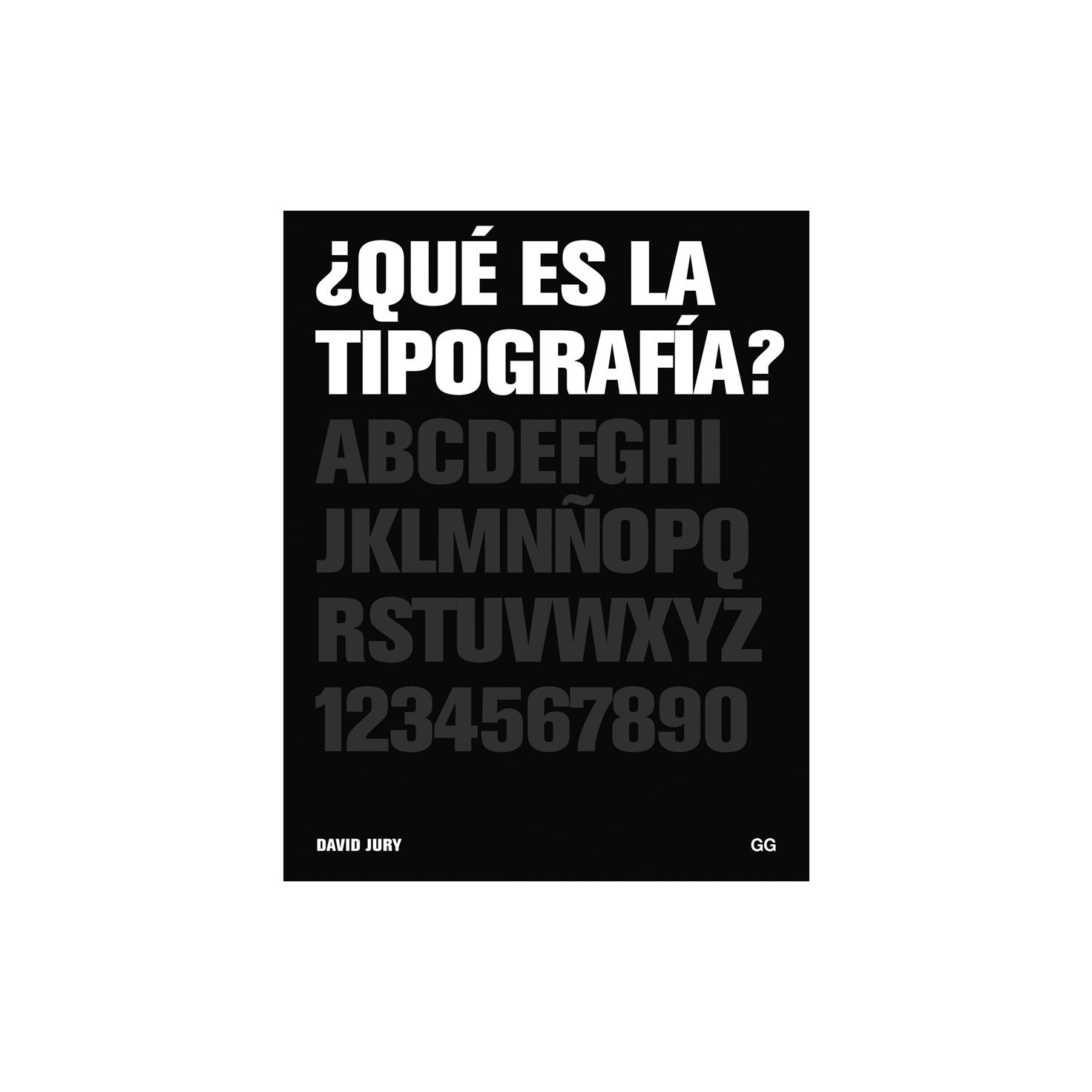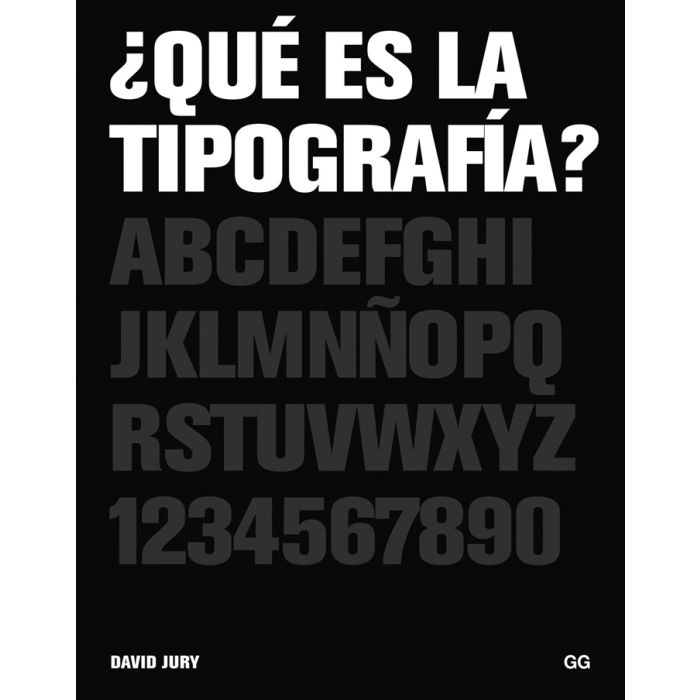
¿Qué es la tipografía?
Un libro de David Jury
El escenario cotidiano en el que la tipografía desempeña su papel clave es invisible, permanece oculto mientras la información se transmite eficazmente. Aunque tradicionalmente ha estado asociada con el diseño y las industrias gráficas, la generalización del acceso a la tecnología digital ha provocado que el término 'tipografía' haya dejado de restringirse a la labor del tipógrafo y se emplee cada vez más para designar el trabajo de organización de un material escrito. Ahora, cualquiera puede ser tipógrafo. Pero si bien las convenciones básicas de la tipografía se aprenden en la escuela, no ocurre lo mismo con los principios elementales del lenguaje visual, y la mayoría de quienes se enfrentan por primera vez a la tarea de diseñar un póster o un folleto descubre (en general con sorpresa) que ni ellos mismos ni su ordenador son capaces de transmitir el mensaje tal y como pretendían.
¿Qué es la tipografía? presenta las estructuras formales de esta disciplina que facilitan el acceso óptimo a la información, sus herramientas, métodos y mecánica; analiza los diferentes soportes existentes y los procesos de reproducción consecuentes y concluye con el análisis de la obra de un ecléctico grupo de tipógrafos que muestra la amplitud, riqueza y calidad del diseño tipográfico en la actualidad.
Índice de contenidos: Temas ¿Qué es la tipografía? La naturaleza de la tipografía Tipografía y lenguaje hablado Tipografía y lectura Tipografía y escritura Tipografía y transformación Autoridad y convención Manuales de impresión y de composición y libros de estilo Reglas y convenciones Oficio y tipografía Hipermedios Visión deficiente Impresión para visión parcial Comunicación comercial Comunicación rural Comunicación urbana Anatomía Semiótica Lingüística Retórica Semántica Grafología Legibilidad Facilidad de lectura Ortografía y pronunciación Alfabetos Puntuación Numerales Distinciones espaciales Textos lineales Composición justificada Saltos de línea no arbitrarios Alineación izquierda Partición de palabras Tipos para pantalla Textos no lineales Información Tipografía efímera Novedad Listas Retículas Kerning, tracking y ligaduras Espacio entre palabras Espacio entre líneas Espacio alrededor del texto Letras cursivas e inclinadas Numerales y versalitas Guiones y barras Paréntesis y corchetes Portfolios A2-Graphics/SW/HK Paul Belford Al Mohtaraf Atelier David Smith Atelier Works Boag Associates Baumann and Baumann Cartlidge Levene David Jury and Fox Ash Jannuzzi Smith Thirteen Lucienne Roberts @ sans+baum SAS UNA (Amsterdam) designers Webb and Webb Design Sam Winston Etcétera Notas Glosario de la puntuación y partes de las letras Glosario general Bibliografía Índice Agradecimientos |
Texto del prólogo: ‘Prólogo Me fascinó aquel catálogo de la exposición celebrada en el Museum of Modern Art de Nueva York en 1964 y 1965 con el título de Architecture without Architects [Arquitectura sin arquitectos]. Su introducción, escrita por Bernard Rudofsky, ataca la visión convencional de la arquitectura que ‘nos presenta con toda la pompa y el boato la arquitectura ‘formal’. La perspectiva discriminatoria del historiador, tal como la conocemos, también está sesgada en el aspecto social... pues se reduce a poco más que a un quién es quién entre los arquitectos que han conmemorado el poder y la riqueza... sin mención alguna de la arquitectura sin pedigrí. Ésta se conoce tan poco que ni siquiera se sabe su nombre. Cabría llamarla vernácula, anónima, espontánea, indígena o rural, según sea el caso’. La belleza de estas construcciones proviene directamente de sus materiales, naturales y locales, puestos en obra con una intervención mínima. La tecnología digital ha transformado la tipografía al posibilitar que cualquier persona se sirva de ella cuando lo desee. El hecho de que la mayoría de quienes trabajan con tipografía (profesionalmente ono) carezca de un concepto ‘formal’ acerca de lo que hace no le resta significado ni valor. Más bien al contrario. Desde tiempos inmemoriales, trabajadores, comercios, servicios de emergencias, amantes y vándalos han sido, por necesidad, los autores de este tipo de señales y mensajes. Ese material se encuentra por doquier y puesto que el título de esta obra formula la pregunta ¿Qué es la tipografía?, he querido explorar en ella los solapamientos, tanto formales como informales, entre la tipografía producida por tipógrafos y la tipografía producida sin tipógrafos.’ Copyright del texto: sus autores Copyright de la edición: Editorial Gustavo Gili SL |